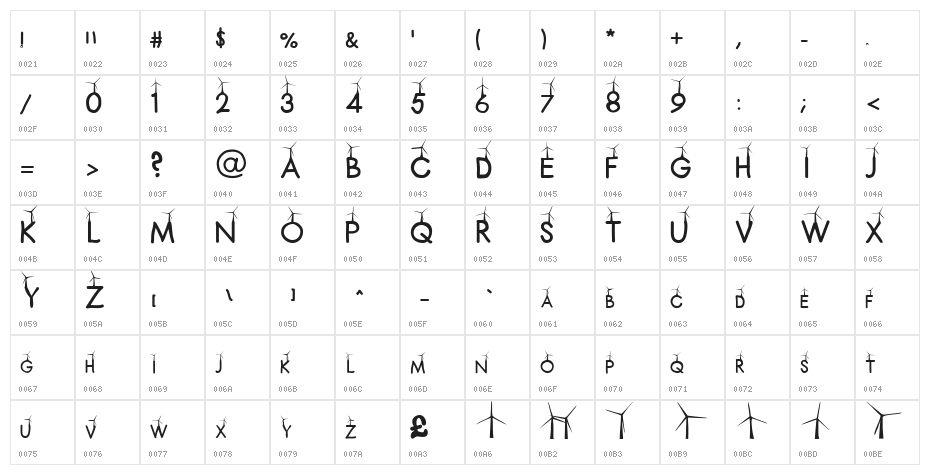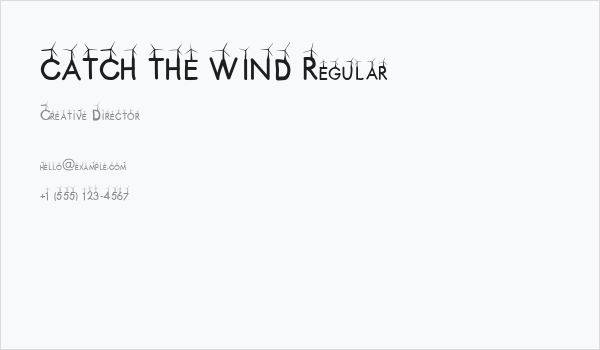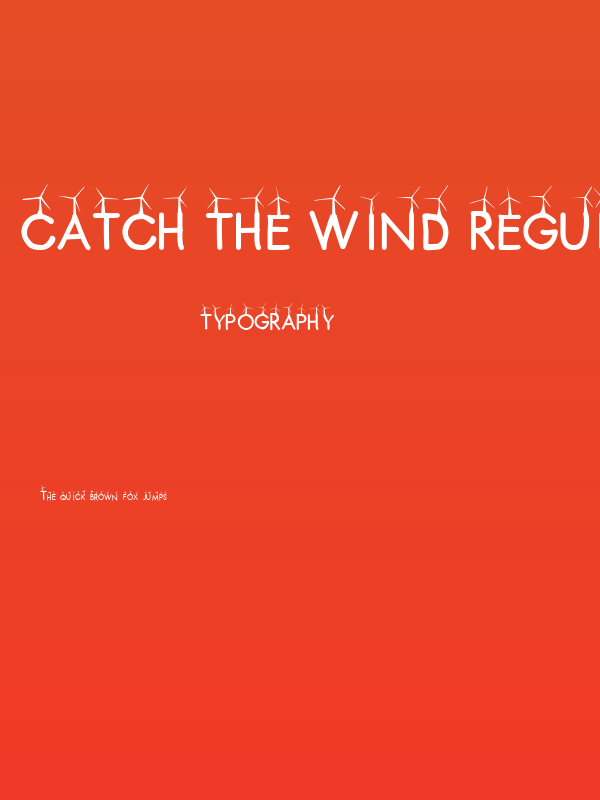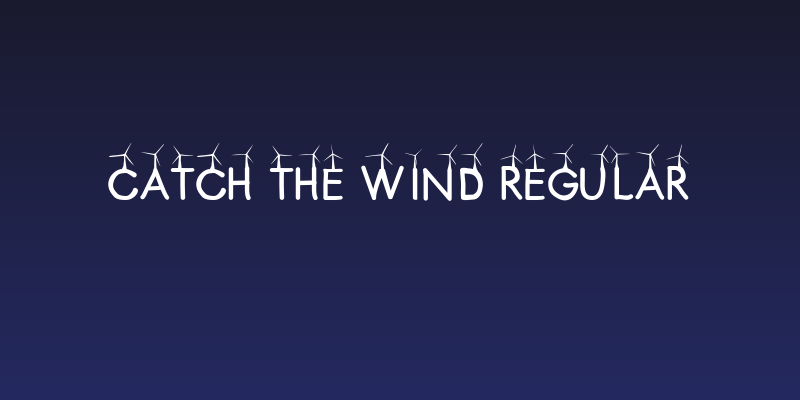
CATCH THE WIND Regular Font
| Vorgeschlagene Projekte | Ideal for eco-friendly branding, environmental campaigns, children's books, and creative posters. |